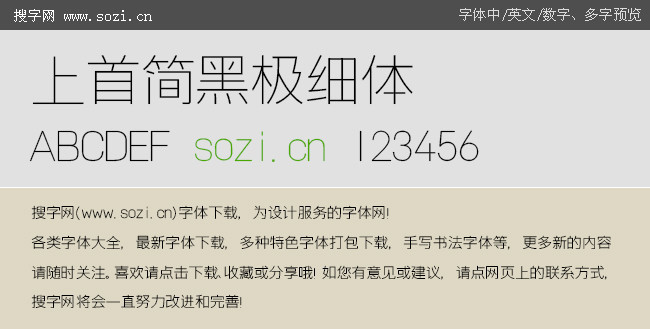
上首簡(jiǎn)黑極細(xì)體
搜字網(wǎng)給大家提供一款上首簡(jiǎn)黑極細(xì)體中文字體下載,上首簡(jiǎn)黑極細(xì)體字形方正,風(fēng)格簡(jiǎn)約,重心平穩(wěn),筆畫極細(xì),給人以平和的感覺(jué),筆劃整齊劃一,可應(yīng)用于各類報(bào)紙、雜志、廣告等正文設(shè)計(jì)。